bộ font MTD Việt Hóa cực đẹp, có chứa rất nhiều font chữ Script Việt hóa với nhiều phong cách khác nhau rất phù hợp để làm typography cho các video âm nhạc Youtube, banner quảng cáo và nhiều loại hình thiết kế khác.
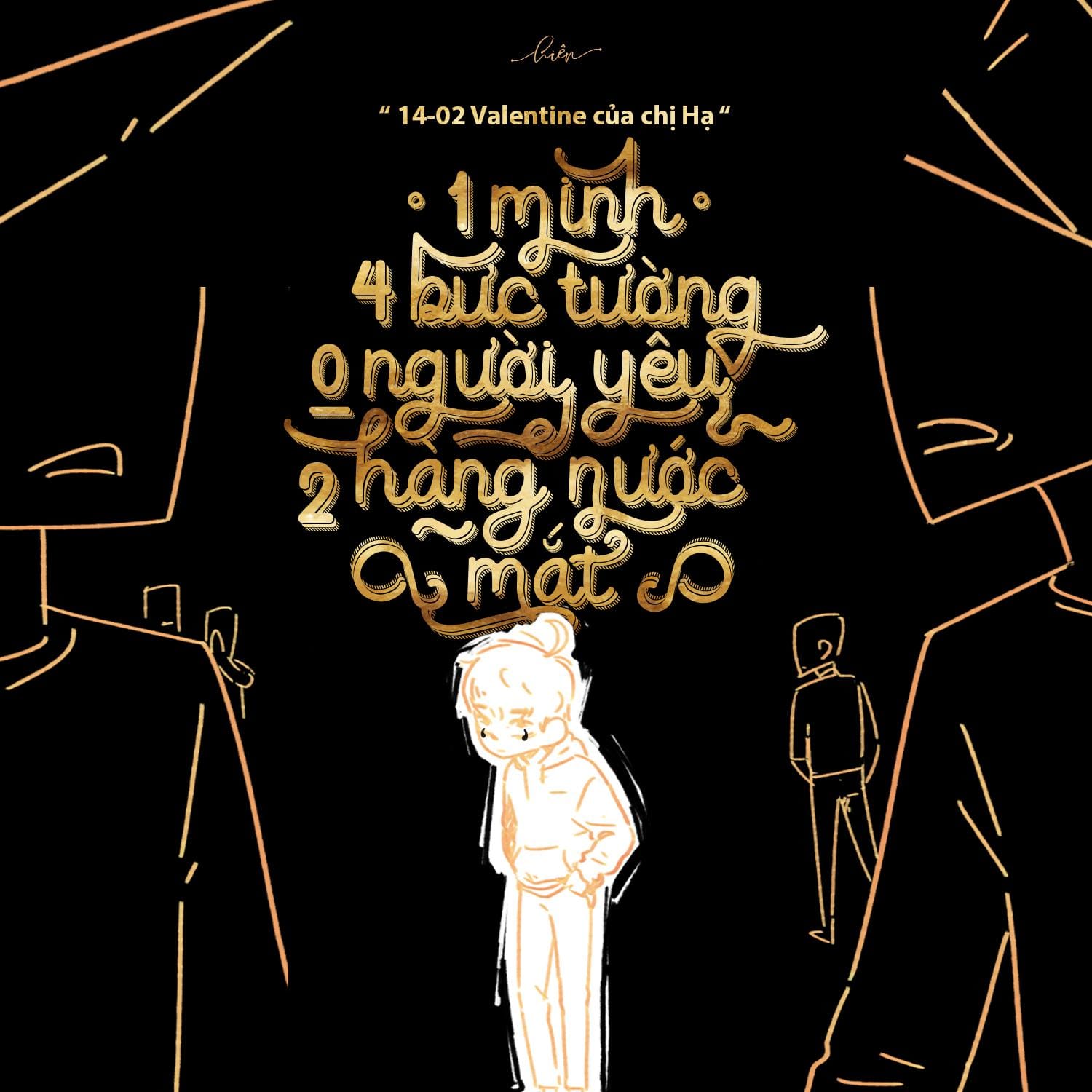
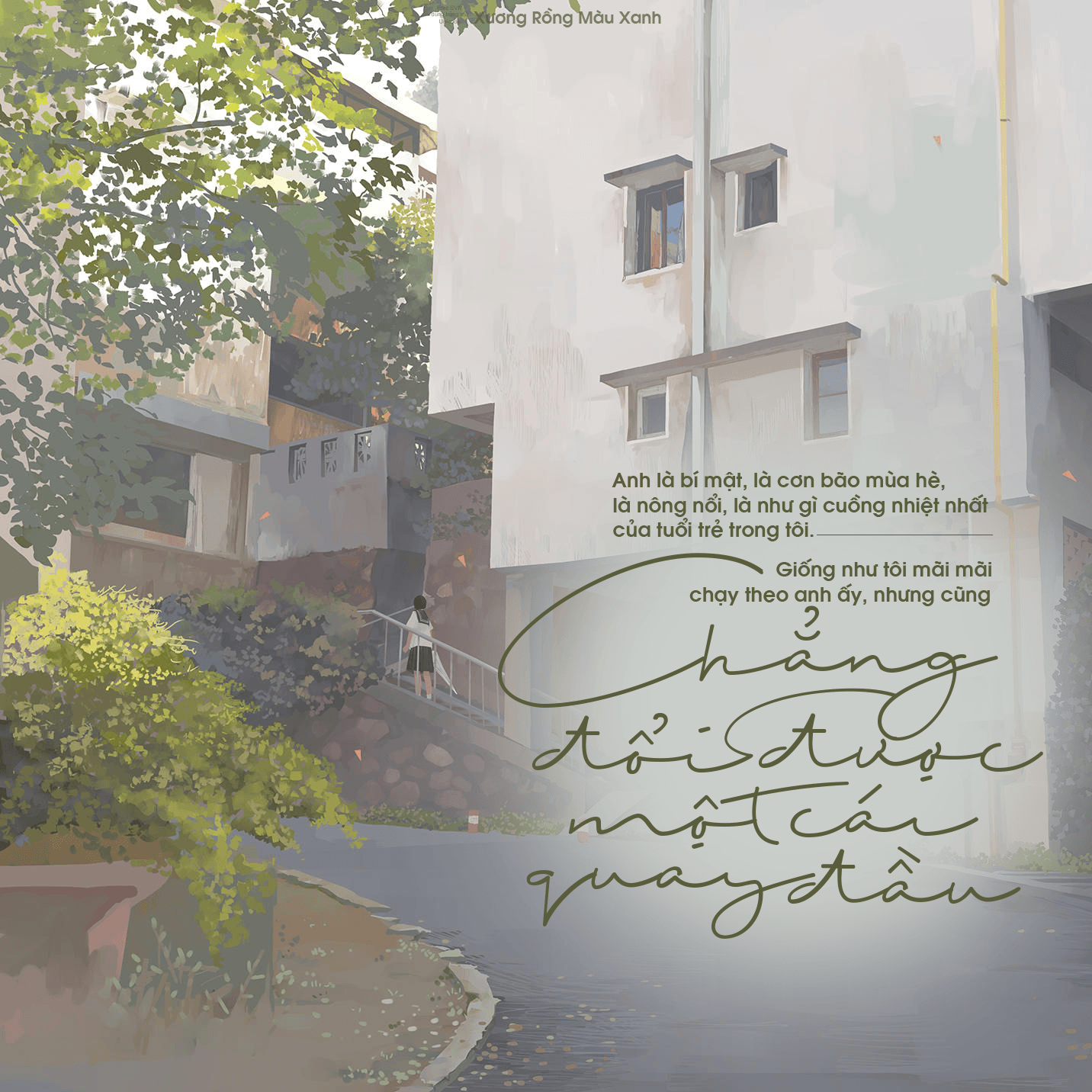
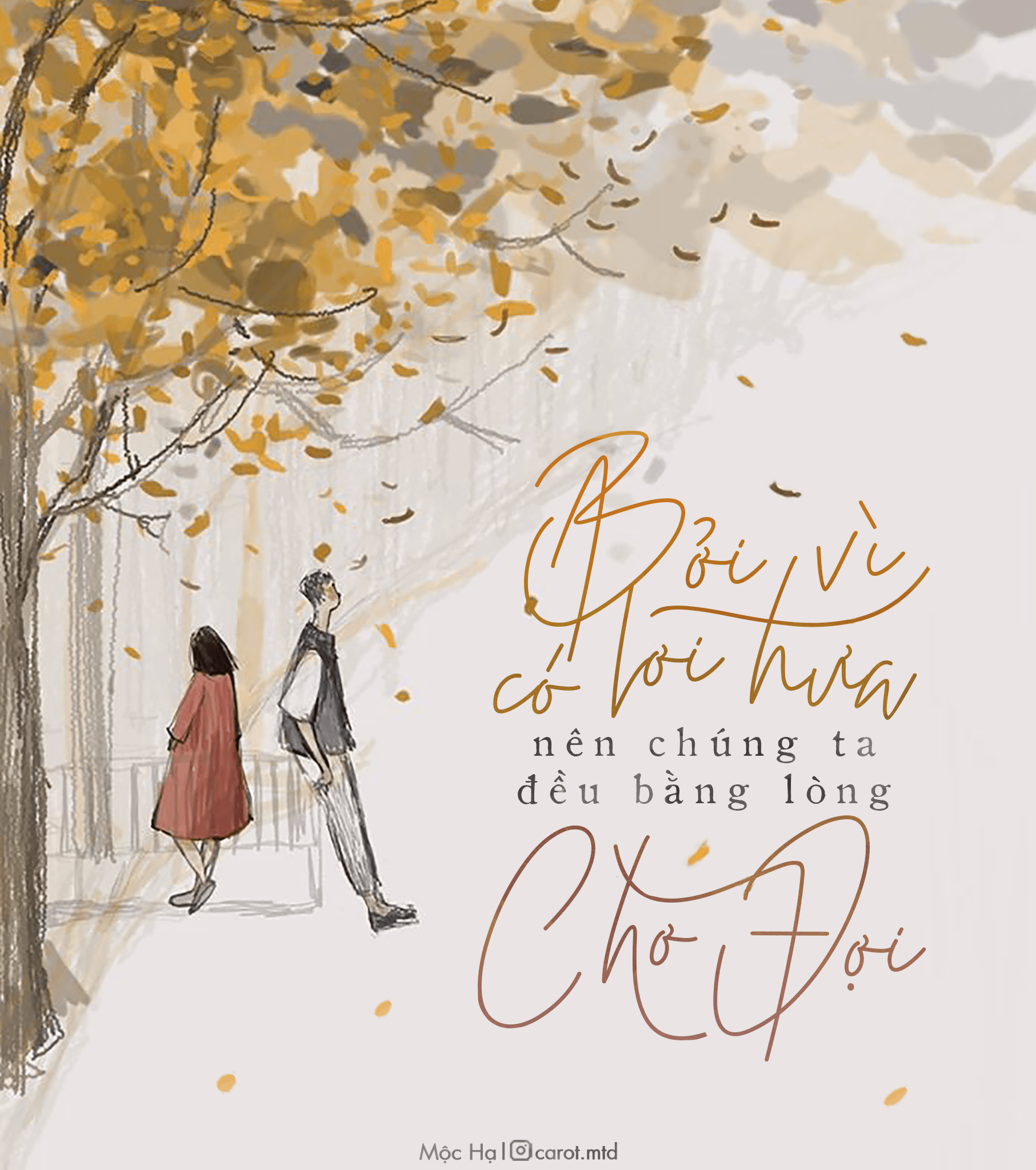
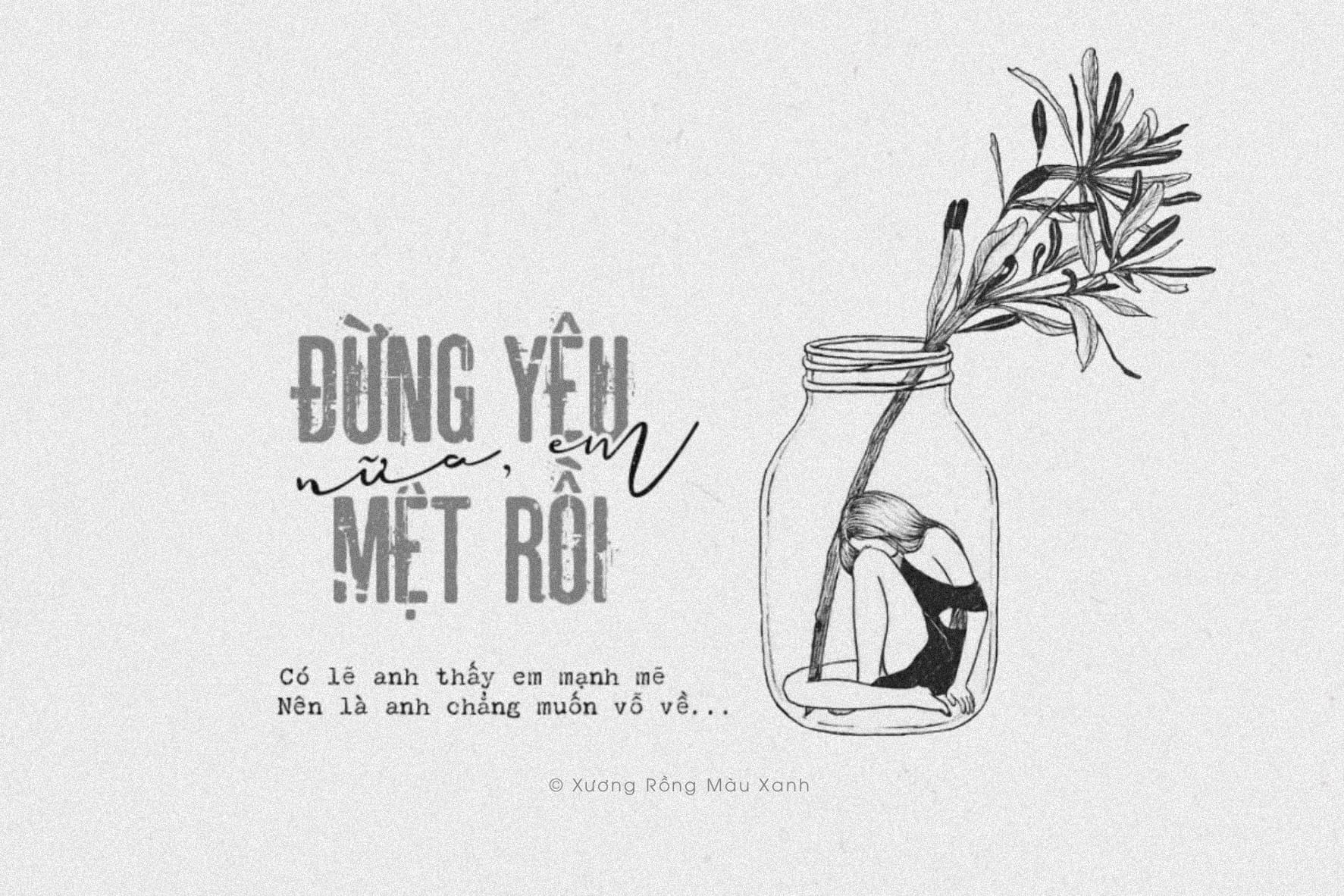
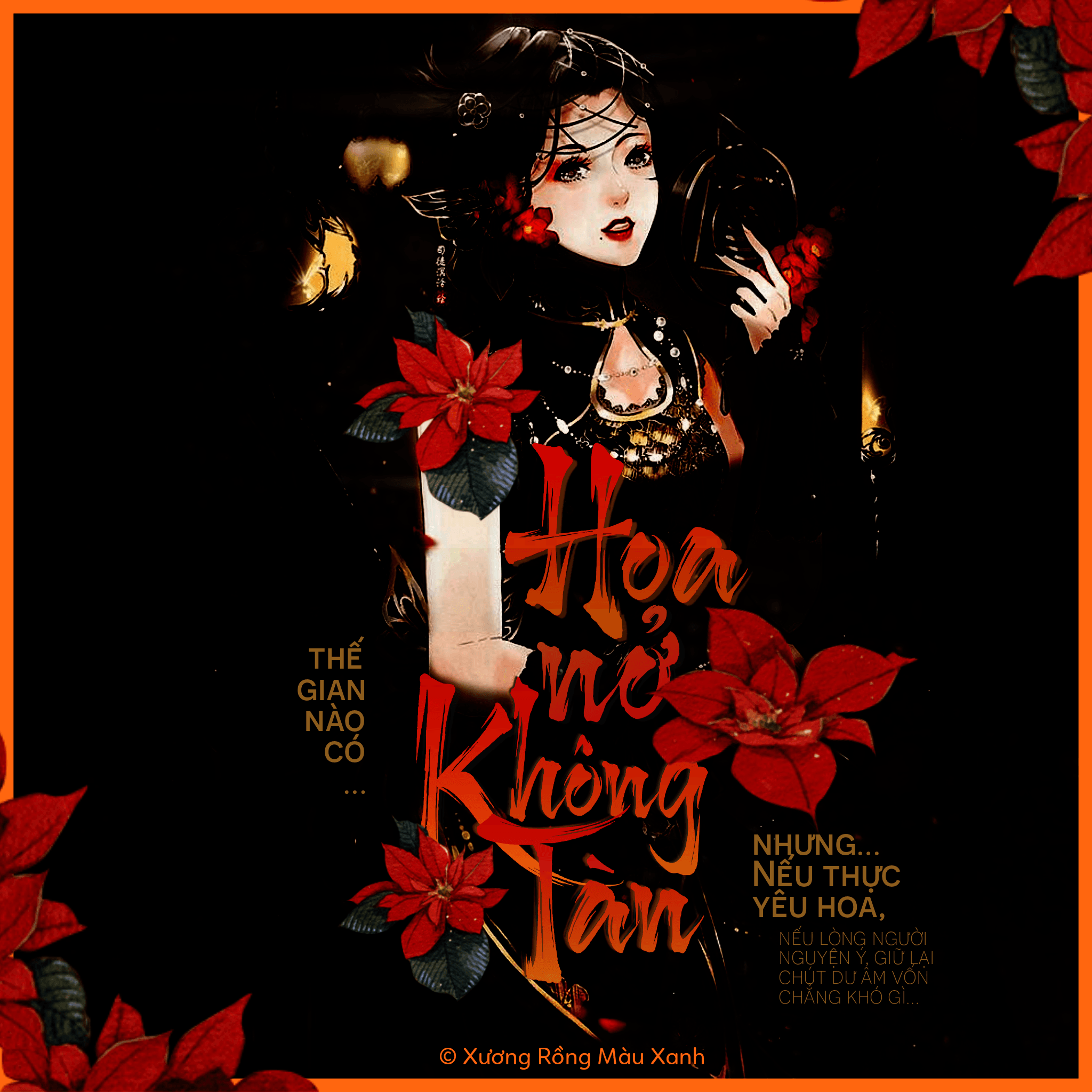
- MTD Adventures Unlimited Sans
- MTD Adventures Unlimited Script Bold
- MTD Adventures Unlimited Script
- MTD Bertolessi
- MTD Caerphilly Regular
- MTD Colatin Swashes
- MTD Colatin
- MTD Danielle Harris Caps
- MTD Douglass Pen
- MTD Familia Script
- MTD Hard Stones Pro Rough
- MTD Hard Stones Pro Strip
- MTD Hard Stones Pro
- MTD Loveya Script
- MTD Sailing Heart Solid
- MTD Sailing Heart
- MTD Shalima
- MTD Shodo Gothic
- MTD Shopping Script
- MTD Summer Cherry
- MTD The Hotelio
- MTD William Letter
- MTD Amstrong
- MTD Candyland
- MTD Feather
- MTD Groovy Script
- MTD Harukaze Slant
- MTD Harukaze Solid
- MTD Harukaze
- MTD Hello Paris Script
- MTD Hello Paris Serif
- MTD High Way
- MTD Kawoszeh
- MTD Kiramba
- MTD Madame Cosmetics
- MTD MagicIvy
- MTD MitreSquare
- MTD Owah Tagu Siam NF
- MTD PI Faded
- MTD QuangNinh_Thuphap_1
- MTD QuangNinh_Thuphap_2
- MTD Simpletune
- MTD SouthPacific
- MTD Stanley Stamp
- MTD Stanley
- MTD WetSpring
- MTD Woolen